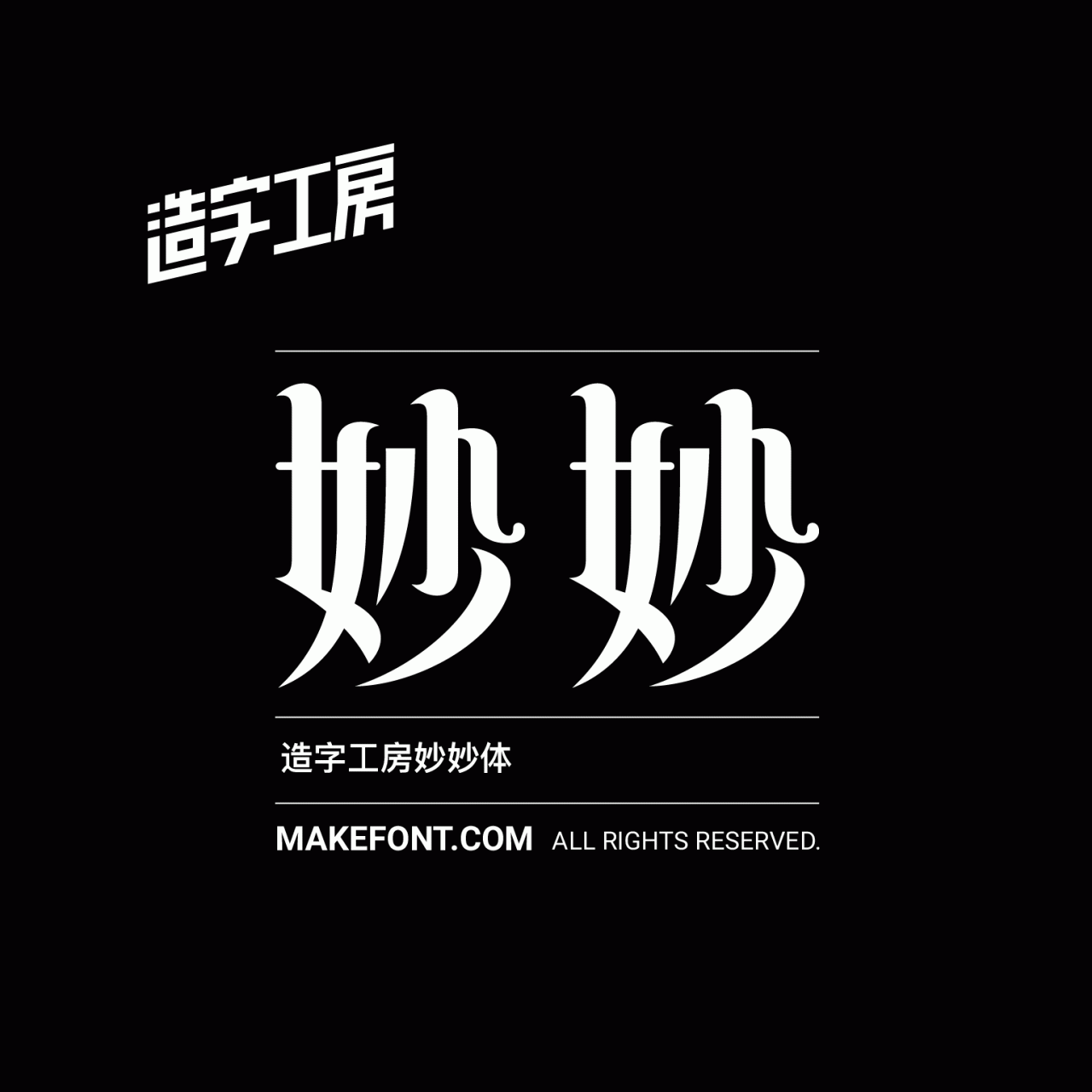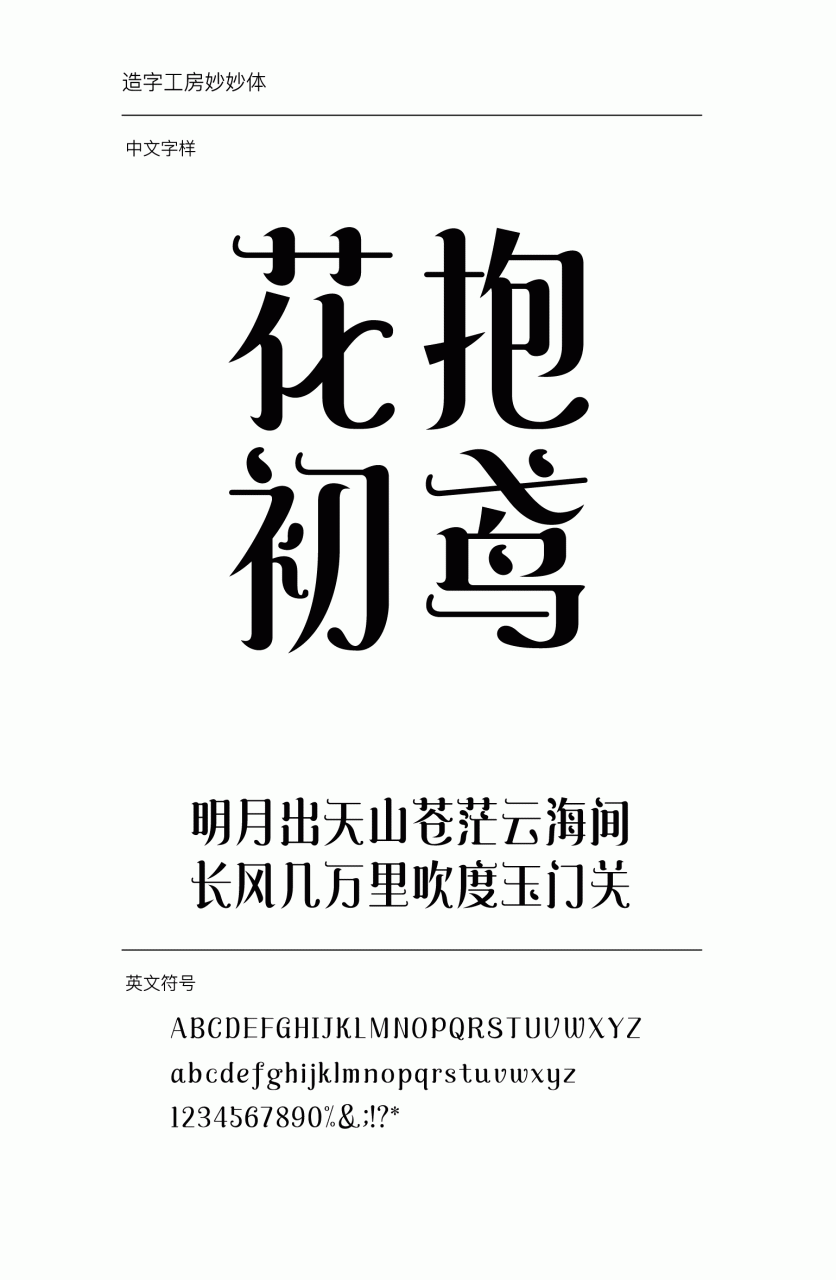
字体简介
造字工房妙妙体,字形活泼、飘逸灵动、端秀清新、特点明确,撇、捺、点、勾大范围的弧度增加笔画的流畅性。捺与钩上特点的添加与横竖笔画特点相互呼应,加上结构的细腻处理使字形更显俊美挺秀之气。具有极强的时尚感。此款字体适用于文字标题、广告设计、企业宣传等视觉环境,有着极强的应用空间。 本字体为简体字库,采用OpenType/CID格式,Adobe-GB1-5编码。基于中华人民共和国GB2312-80字符集标准,另按需添加101个汉字。共收容字数6864CJK汉字,ASCII常用字符100个。